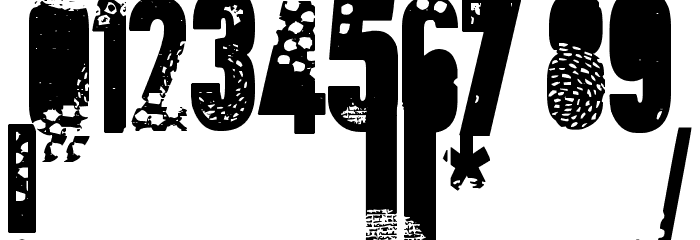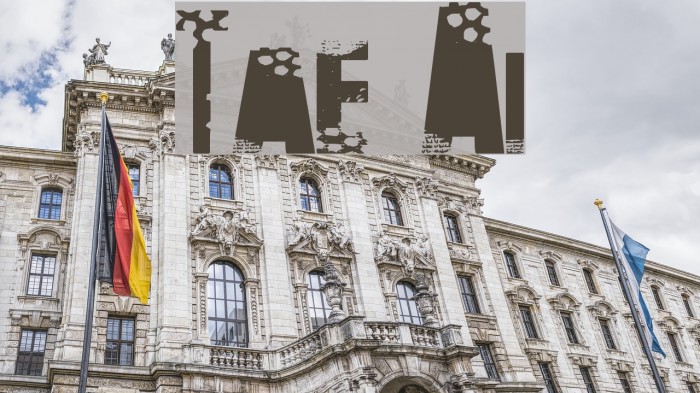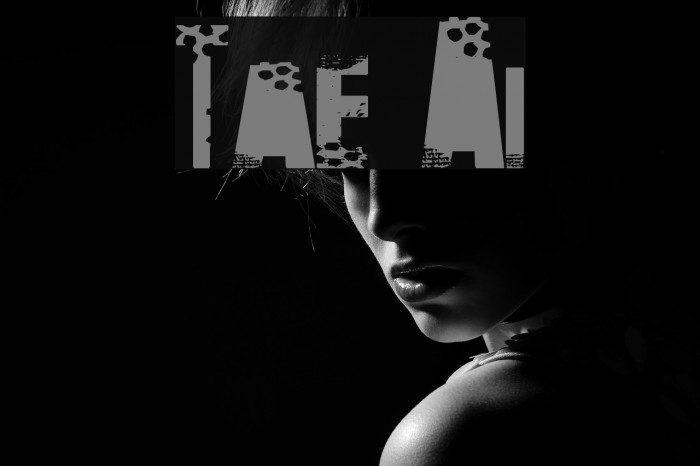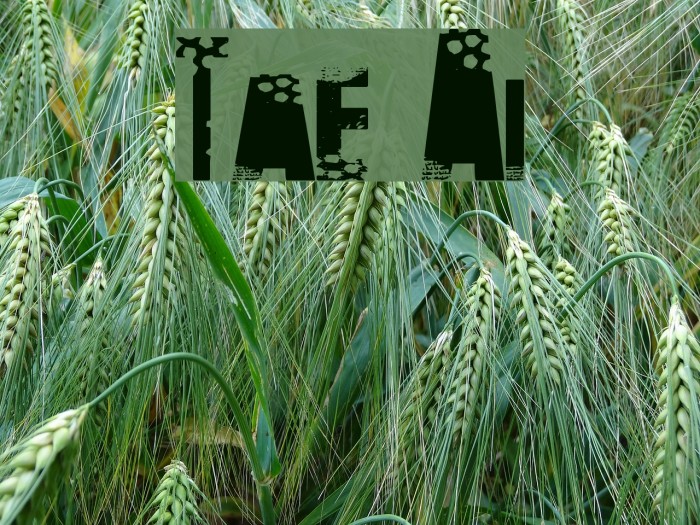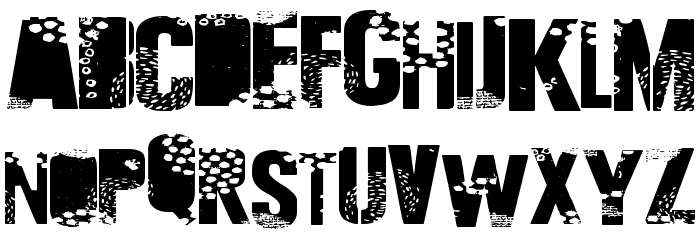
Talvez Assim Font
✎ Decorative
| Estilo general | Grunge, Edgy |
| Proyectos propuestos | Ideal for album covers, posters, streetwear branding, and any design needing a bold, edgy look. |